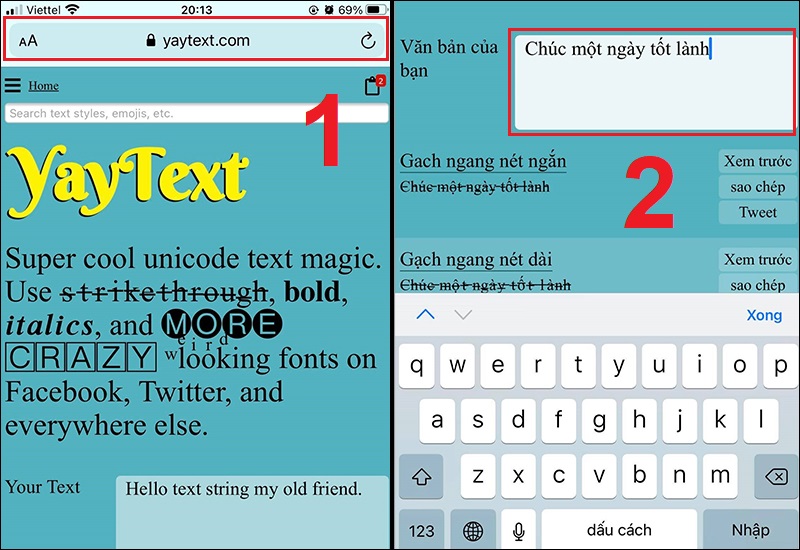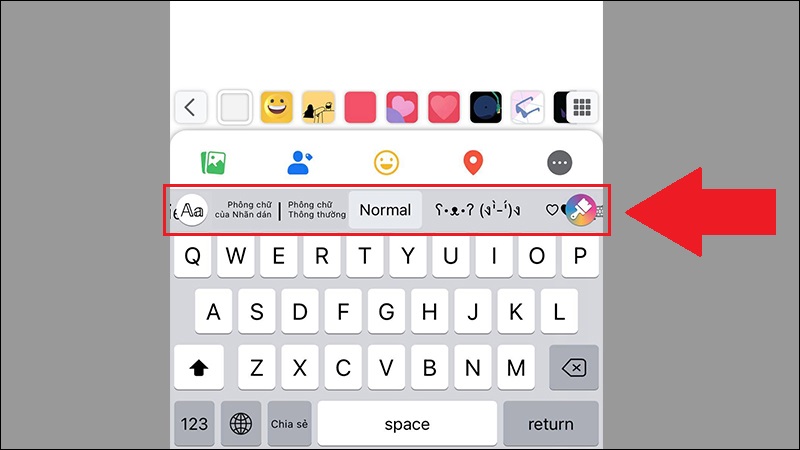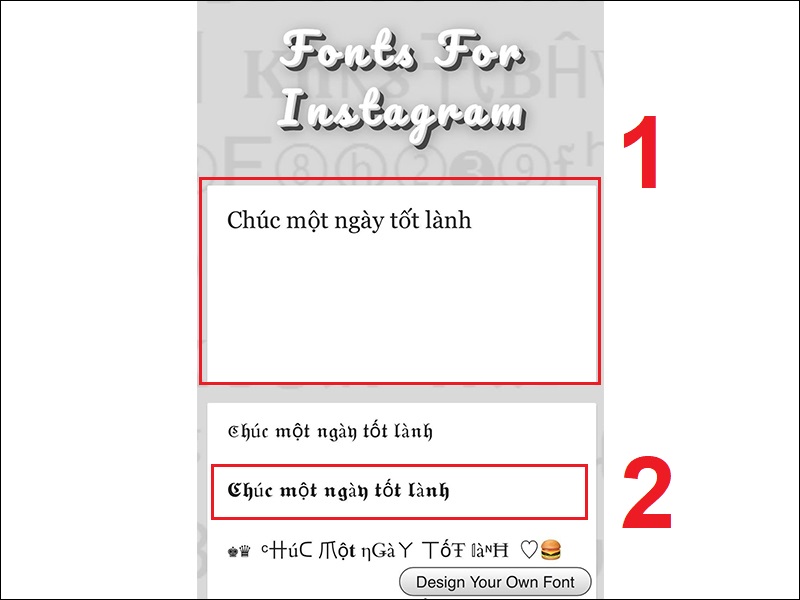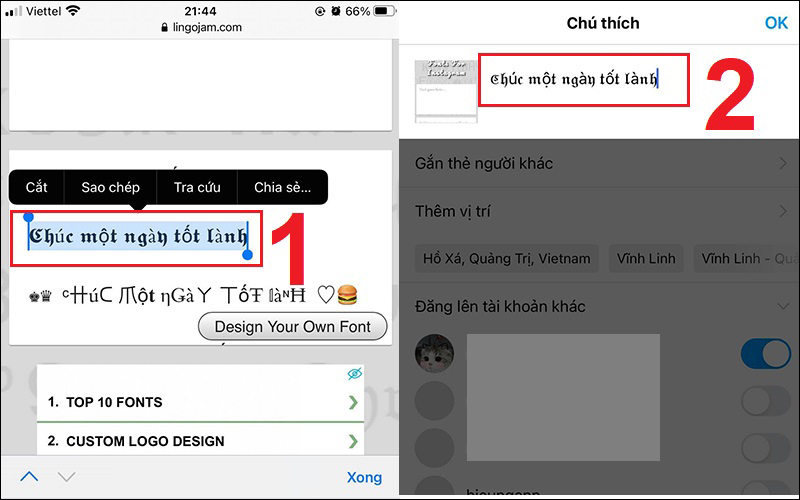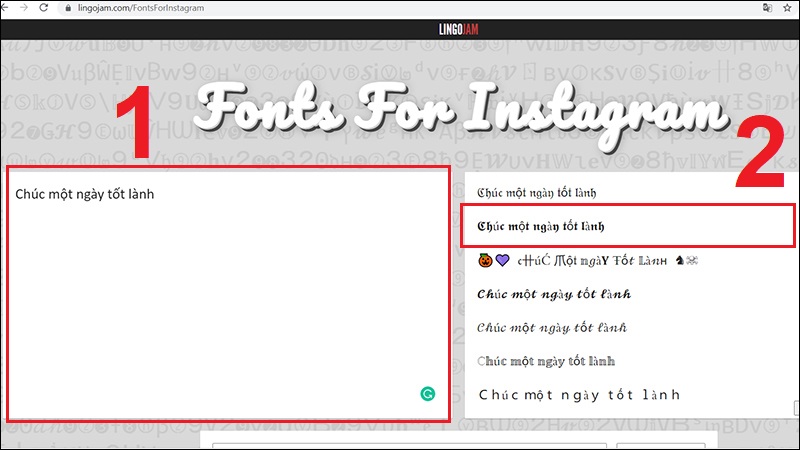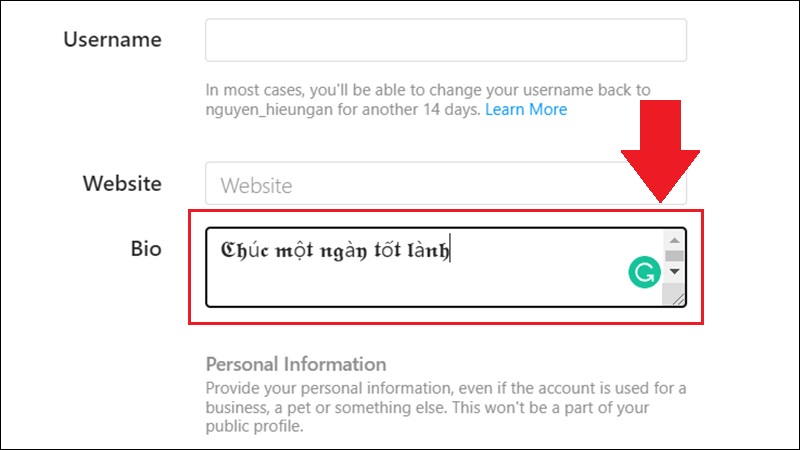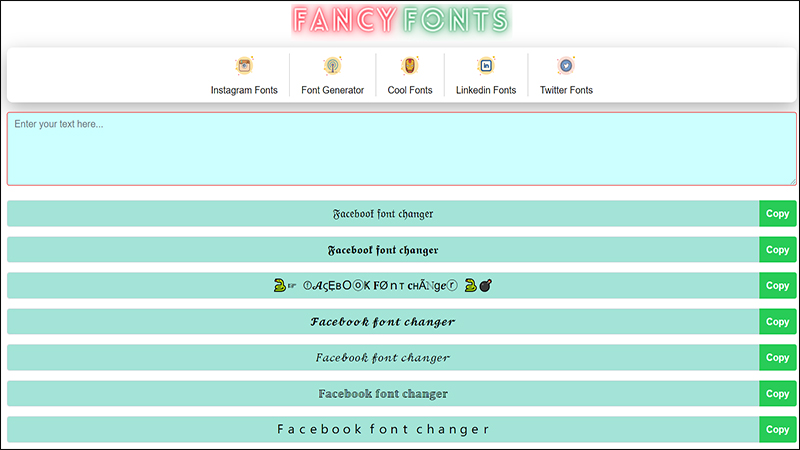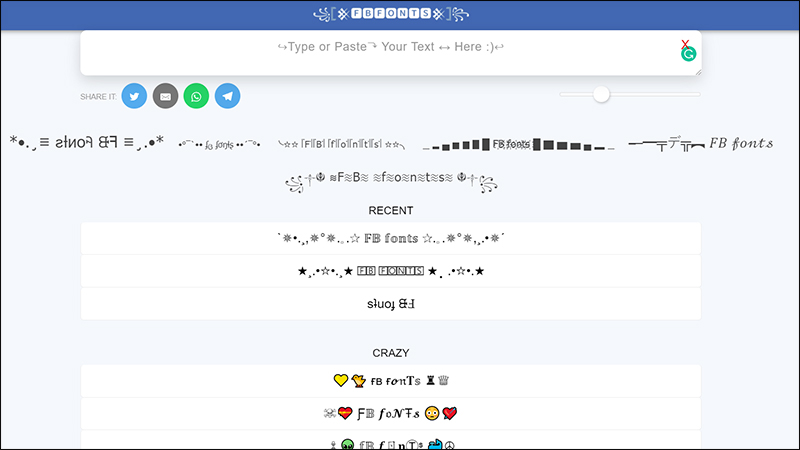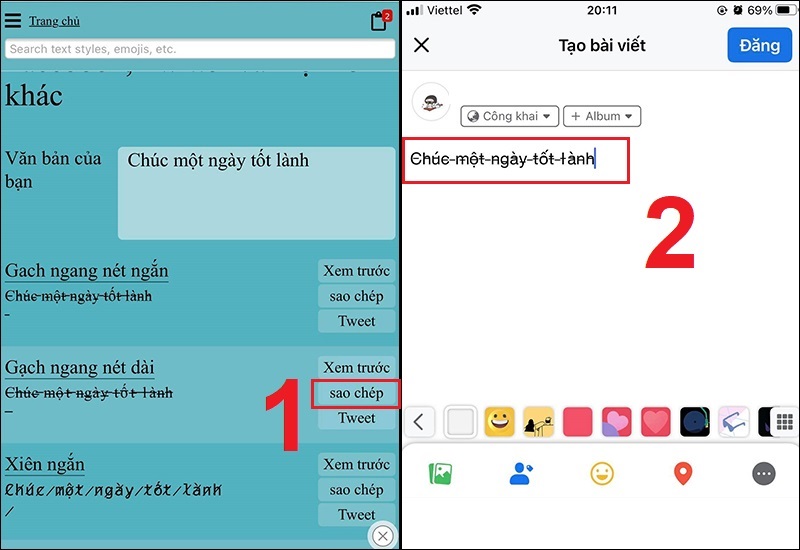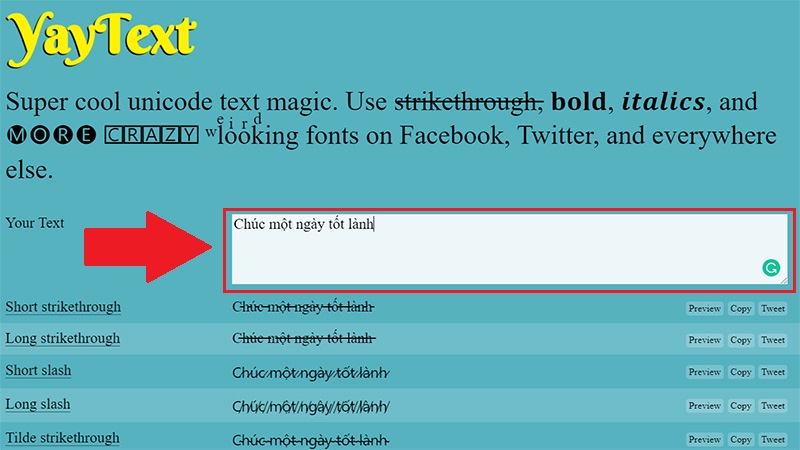
Cách viết chữ kiểu, font chữ khác trên Facebook, Instagram siêu xinh Update 09/2026
Đôi khi trên Facebook hoặc Instagram, bạn sẽ bắt gặp các bài đăng hoặc status của ai đó có một phông chữ lạ làm bạn thích nhưng bạn không biết phải làm thế nào để có thể viết được như thế. Vậy thì bài viết dưới đây sẽ hướng dẫn các bạn cách viết chữ kiểu, font chữ khác bằng điện thoại hoặc máy tính để bạn có thể thiết kế những bài đăng ấn tượng. Đừng quên ghi chú những điều quan trọng vào laptop của mình nhé!
1. Cách viết chữ kiểu, font chữ khác trên Facebook
– Cách viết phông chữ khác trên Facebook bằng Yaytext
YayText là một công cụ tạo kiểu cho văn bản trực tuyến. Văn bản được tạo ra bởi YayText có thể được sử dụng trực tuyến ở bất kì nơi nào. Các font chữ của Yaytext rất đẹp và độc đáo như chữ in đậm, in nghiêng, chữ nhỏ, gothic, bong bóng,…
+ Trên điện thoại
Bước 1: Truy cập trang web yaytext.com > Gõ văn bản bạn muốn chỉnh sửa vào hộp Văn bản của bạn.
Gõ văn bản bạn muốn chỉnh sửa
Bước 2: Nhấn nút sao chép bên cạnh văn bản bạn muốn sử dụng > Vào ứng dụng hoặc trang web bạn muốn sử dụng văn bản và dán văn bản đã chỉnh sửa vào.
Dán văn bản vừa chỉnh vào trang web hoặc ứng dụng bạn muốn
+ Trên máy tính
Bước 1: Truy cập trang web yaytext.com.
Bước 2: Nhập đoạn văn bản cần chỉnh font vào khung Your Text.
Nhập văn bản cần chỉnh vào khung Your Text
Bước 3: Nhấn copy bên cạnh văn bản bạn muốn sử dụng.
Nhấn copy văn bản bạn thích
Bước 4: Vào ứng dụng hoặc trang web bạn muốn sử dụng văn bản và dán văn bản đã chỉnh sửa vào.
Dán đoạn văn bản vừa tạo vào nơi bạn muốn
Lưu ý: Với Tiếng Việt thì một số font chữ sẽ gặp lỗi nhẹ với một số từ có dấu hoặc với một số điện thoại đời cũ.
– Các cách viết chữ kiểu trên Facebook khác
Ngoài Yaytext, còn có một số website để bạn có thể viết chữ in đậm, in nghiêng, đổi font chữ Facebook.
+ Fancy Font
Website cho phép bạn chỉnh font chữ cho nhiều ứng dụng khác nhau như Instagram, Facebook, Twitter. Fancy Font có giao diện dễ sử dụng, nhiều font chữ đẹp, độc đáo để bạn lựa chọn.
Fancy Font có rất nhiều font chữ ấn tượng
+ Facebook Fonts
Tương tự như Yaytext, Facebook Fonts cũng cung cấp rất nhiều font chữ độc đáo, lạ mắt để bạn có thể viết những bài đăng hay status cực “chất”.
+ FBFONTS
FBFONTS có một kho font chữ vô cùng đa dạng và ấn tượng, ngoài font chữ còn có rất nhiều biểu tượng cảm xúc, kí hiệu dễ thương và thú vị.
FBFONTS có rất nhiều font chữ và emoji độc đáo
– Cách viết phông chữ khác trên Facebook qua ứng dụng
Ứng dụng Fonts
Đây là ứng dụng thay đổi font chữ dành cho các thiết bị Android và iOS.
Fonts hoạt động trên Instagram, Telegram, Facebook, Messenger, TikTok, WhatsApp và nhiều ứng dụng khác.
Ứng dụng cho phép bạn thay đổi font chữ nhanh chóng, tiện lợi. Có rất nhiều font chữ đẹp, độc đáo với nhiều phong cách đa dạng như chữ in đậm, in nghiêng, gothic, emoji cho bạn thỏa thích lựa chọn.
Ưu điểm: Cách này sẽ giúp các bạn có thể thay đổi font chữ nhanh hơn, tiện lợi hơn. Bạn chỉ cần vào ứng dụng thao tác là có thể có được font chữ như ý mà không cần phải nhớ hay tìm kiếm lại đường link để truy cập các trang web.
Ứng dụng Fonts giúp tạo kiểu chữ nhanh chóng, ấn tượng
Gạt nút sang phải để cấp quyền cho ứng dụng Fonts
+ Cách sử dụng Fonts
Bước 1: Tạo bài viết trong ứng dụng bất kỳ (Trong hướng dẫn là Facebook) > Trong giao diện bàn phím nhấn giữ vào biểu tượng quả cầu > Chọn Fonts.
Chọn Fonts để kích hoạt ứng dụng
Bước 2: Trượt sang trái phải và chọn font chữ bạn thích và thực hiện viết chữ như thường.
Chọn font chữ bạn thích và bắt đầu viết văn bản
2. Cách viết chữ kiểu, font chữ khác trên Instagram
Fonts for Instagram là một ứng dụng cho phép bạn thay đổi font chữ thông thường trên Instagram thành các font chữ độc đáo lạ mắt. Điểm nổi bật của Font for Instagram là kiểu chữ thú vị hơn với nhiều phong cách nghệ thuật kèm theo đó là những biểu tượng cảm xúc khác nhau.
Ưu điểm của Fonts for Instagram là rất tiện lợi, dễ sử dụng, kho font chữ rất lớn và độc đáo, bao gồm các font in đậm, in nghiêng, nghệ thuật, gothic hay cả các emoji.
Bạn hãy mở trang Instagram của mình > Chọn mục Chỉnh sửa trang cá nhân > Dán font chữ mới này vào và nhấn Xong.
– Trên máy tính
Bước 1: Truy cập Fonts for Instagram.
Bước 2: Nhập văn bản của bạn vào ô trống bên trái > Sao chép font chữ bạn thích.
Sao chép font chữ bạn muốn
Bước 3: Dán đoạn văn bản vừa tạo vào Instagram.
Dán đoạn văn bản vừa tạo vào Instagram